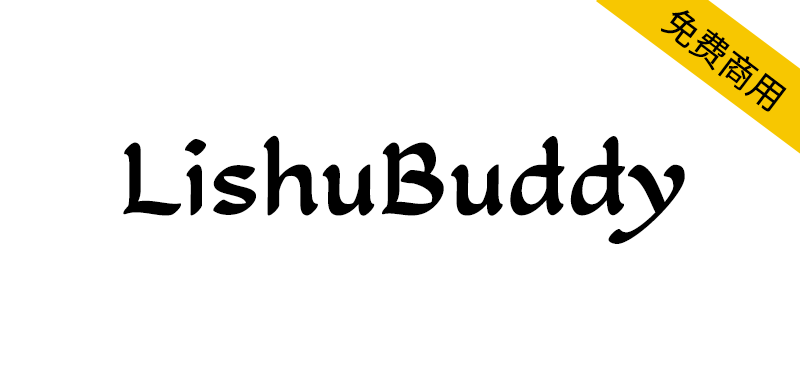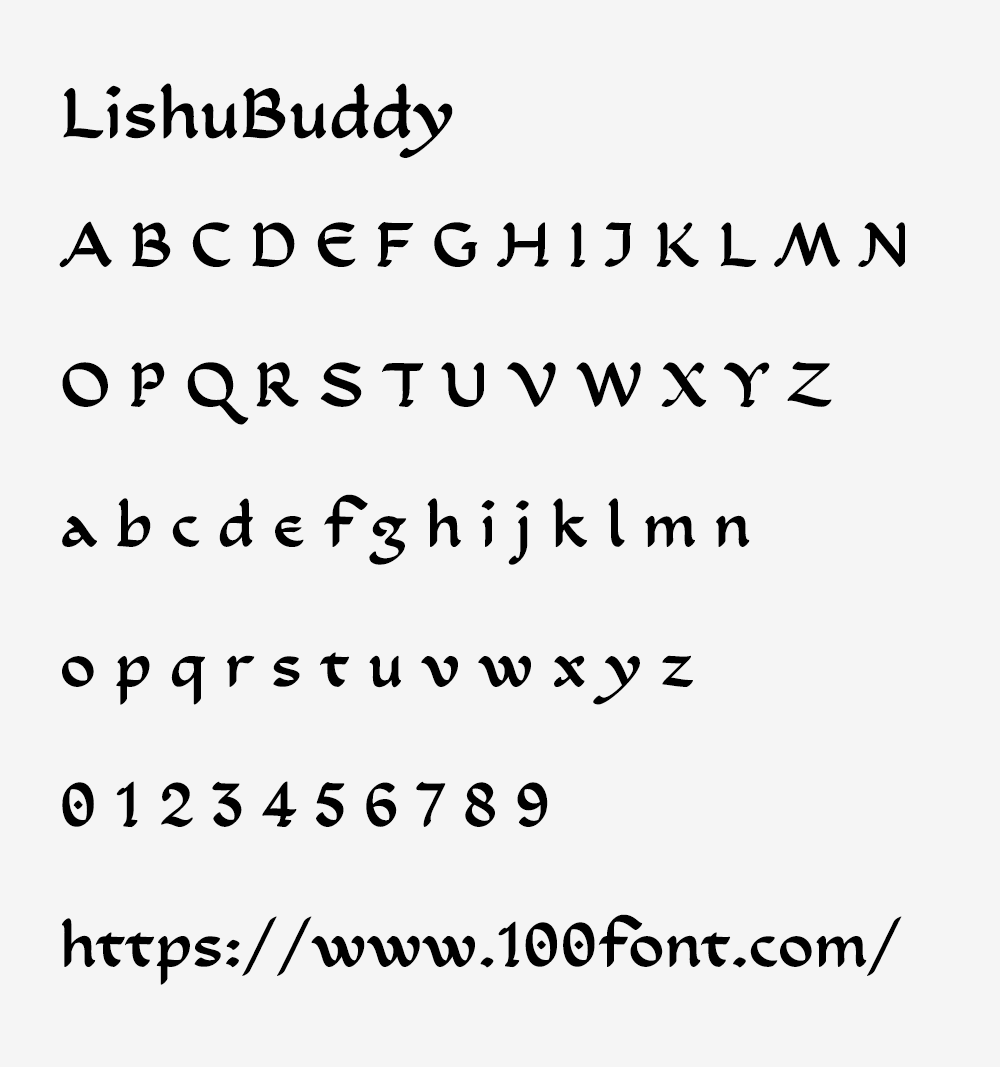
由于隶书有很多变体,鉴于参赛要求(汉仪字体之星大赛),采用汉仪中隶书作为中文正文。选用汉仪中隶书的意义在于:汉仪中隶书、方正隶二、华文隶书其实都长得一样(不知道谁向谁致敬),这样,西文就具有通用性。隶书笔画的特点是“横”的一波三折,也是汉字中古老的字体形式,保留了较为原始的手写风格,因此,希望能够在西文中找到较为原始的手写字体来进行风格匹配,查阅了西文字体发展史,最终决定使用西文的Carolingian Minuscule的字体风格来进行设计,Carolingian Minuscule 卡洛林小写体——法兰克王国的手写体。
法兰克王国是法兰克人在西欧建立的王国。5 世纪末,克洛维统一了法兰克人,于 481 年建立了墨洛温王朝。之后经历数次分裂和统一,由丕平三世于 751 年创建了卡洛林王朝,并在丕平三世之子查理大帝时期迎来了最强盛时期。 查理大帝 (742—814) 是法兰克王国加洛林王朝国王(768—814 在位)。顺便提一下,他的名字用法语称「查理曼」(Charlemagne)、英文称查理大帝 (Charles the Great),德语称「卡尔大帝」(Karl der Große)。他大幅扩张版图,统一了日耳曼各部,由教皇加冕为西罗马皇帝(800—814 年在位),从国王变为了大帝。 查理大帝在统一中央集权整备法制的同时召集了欧洲各地学者振兴学术文艺。这个文化繁荣的时期被史学家称为「卡洛林文艺复兴」。尽管这个时代羊皮纸价格不菲,书籍的需要依然居高不下。查理大帝从约克叫来了高僧阿尔昆[3]并提拔他为图尔的圣马丁大修道院院长。
阿尔昆在修道院里开设了抄写室,将罗马时代后期安色尔体 (uncial) 改为小写的半安色尔体再进行改进,形成了一种新的字体,这就是卡洛林小写体(Carolingian minuscule)。仔细观察,卡洛林小写体的横笔画也有一波三折的特点,这一点很妙。而且作为拉丁字母发展初期的原始字形,有着很强烈的手写特点。
解决方案:1、字形结构偏扁宽,笔画粗细对比较为均匀,与隶书的气质协调,版面灰度均衡;2、强化西文横笔画中的波磔,甚至在一些弧线末端也进行了横向的处理,如c、d、e、k、q、s、C、E、F、G、S、J;3、在西文设计中,使用super brush来模拟鹅毛笔的书写规律,考虑到隶书笔画横粗竖细的特点,将super brush的斜角调整为45度(常规为30度),得到较为均匀的横竖对比;4、为配合隶书笔画的粗糙化效果,单独设计了粗糙化(rough)的style,以及单独设计了中文标点,考虑到西文字体有单独使用的场景,不能使用中文标点的字宽,因此将中文标点单独设计为独立的style,因此,本字体家族共有3款风格:regular、rough、Chinese Punctuation,可以在indesign中通过复合字体搭配使用;5、对于这种手写字体,字间距kerning(字距微调)就变得非常重要,需要进行精心调整,才能达到协调完美。
总结:1、西文字体设计并不仅仅是26个字母那么简单,比我之前想象的要难。字体部件的引用和变化,是保持整个字体DNA的统一的关键;2、Fontlab 这款专业软件,功能相当强大,有些功能甚至于比AI还要好用,但是全英文界面,而中文互联网上几乎没有相关教程,全靠online help guide和自己摸索。油管上有官方视频,但是……你懂的,总之,学习成本很高;3、字距(spacing)和kerning(字距微调)是之前完全没有接触过的概念,同时也是最花时间的环节,作为初学者,还有很大的提升空间;4、opentype的很多功能仍需要进一步摸索。